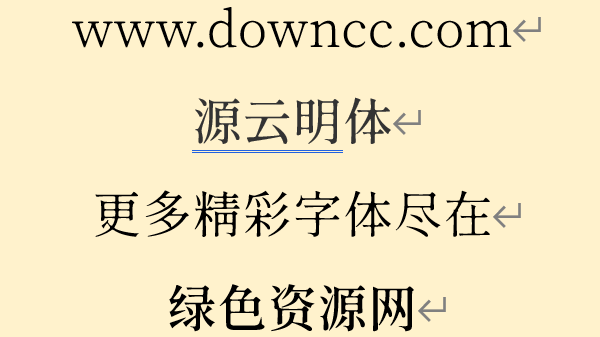
源云明體ttf字體為你提供了一整套字體,可以說是字體包。其中的字體由思源字體改編,通過加入不同的元素為進行一一展現。字體包比較大,下載完成之后解壓全部安裝就行了。歡迎下載!
源云明體是一款字體包,該字體庫源自思源字體,并且從原先的源樣明體基礎上進行改造,筆畫之間更多的接連,增添整體感,本字體開源免費商用
1、四個權重
現在,Light Regular·Medium·SemiBold的4個權重已經改造完成。我覺得可以廣泛運用。
3、墨汁處理
進行了更加滲入“源云明朝”的處理,過分抑制了數碼字體容易出現的銳氣。
這款字體是臺灣最活躍的字型社團「字嗨」管理員 But Ko 釋出的,總共有三款改造自思源宋體的繁體中文字體,開放給需要的使用者免費下載!三款字體分別為:源樣明體、源流明體及源云明體
這三款字體的共同特色是修改自「思源宋體」,源樣明體采用思源宋體韓文版本的字符,配合繁體中文習慣的置中標點符號,可說是兼具排版及傳統(tǒng)印刷體風格的繁體中文字體;源流明體在筆畫上有所調整,使字型看起來更有力道;至于源云明體在橫筆的起筆及豎筆的起筆、收筆處加入粗細變化,筆畫交叉處有朦朧處理。字體改造雖以計算機程序自動進行,但在一些細節(jié)調整后可以明顯感受出不同效果。若有興趣可參照以下鏈結及教學來下載。